Itt a karácsonyi időszak, és mindenhol karácsonyi gömbökkel és díszekkel van tele az internet. Ezek egyik speciális fajtája, amikor egyedi feliratú gömböt tudsz rendelni. Azonban mostantól erre nem lesz szükséged, mutatom, hogyan tudod elkészíteni magadnak vagy családodnak, barátaidnak. Természetesen a karácsonyi gömbökre kalligrafálni fogunk, hiszen mindent is lehet kalligráfiával díszíteni, csak ismerni kell a trükköket. Mutatom is őket, de előbb nézzük meg mi is kell a karácsonyi gömb díszítéséhez.
Mire is lesz szükséged a karácsonyi gömbökhöz?
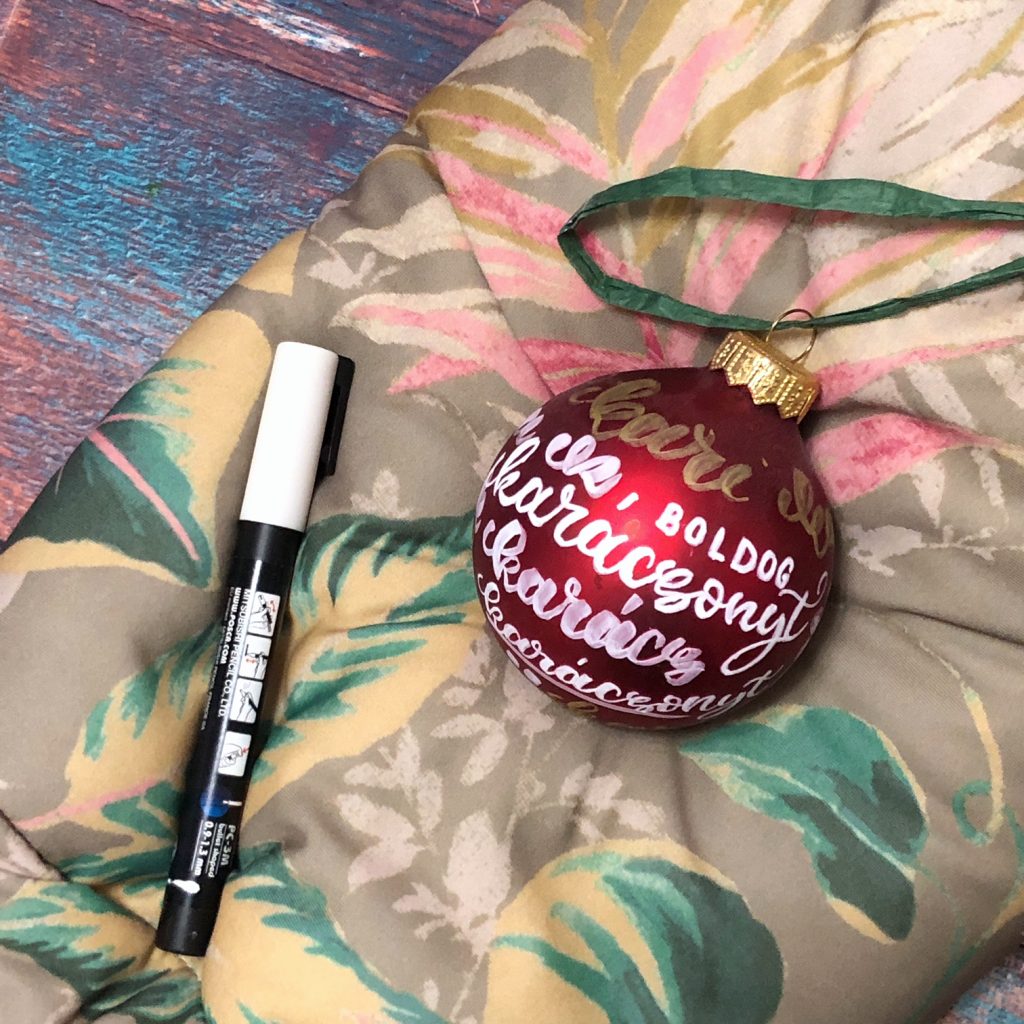
A díszítés
A karácsonyi gömbhöz ugyanazokat a trükköket fogjuk használni, mint korábban a bögrénél. Szóval, ahogy a bögrénél is írtam a lényeg, hogy találd meg azt a pozíciót, amivel alá tudod támasztani kezedet. Erre többféle verziót láttam, van, aki dobozokat tesz a keze alá, nekem a babzsák jött be igazán.
Ezután érdemes a fényes gömböknél alkohollal áttörölni felületet, hogy ne legyen rajta semmi zsír. Az íráshoz még érdemes valami kis könnyed kesztyűt használnod, hogy ahogy leérinted a kezedet ne legyen zsíros utána. A legegyszerűbb változat egy használt zokni kivágása úgy, hogy a gyűrűs és a kisujjad legyen benne. Nekem a Sheinről rendelt változat van, sok esetben hasznos.
Természetesen érdemes hamis kalligráfiát, akarom mondani letteringet használni. Kicsit meg is ugráltatni a betűket, mert így lehet „csalni” kicsit az egyenessel. A gömb esetében érdemes a pocakjára írni, azaz ahol a leghosszabb a körmérete, így itt van a legnagyobb felületet az írásra.
Érdemes akár a betűtípusokat keverni, mint ahogy én is tettem. Rád van bízva, hogy melyik verziót választod, nyilván függ attól is, hogy mennyi szöveget szeretnél ráírni. Összességében azért ezekre a 6-8 cm-es gömbökre maximum 1-2-3 szónál többet nem lehet írni, mert nem lesz túl olvasható, illetve neked is sokkal nehezebb dolgod lesz. Legalábbis ez a tapasztalatom, hogy a 4-5 mm-es ovális méret alatt egyre nehezebb az írás.
Szóval, ha meg van a szöveg, akkor helyezd a bögrét a zsákra és helyezkedj el az íráshoz. Ahogy írtam a bevezetőben is használhatsz akvarell ceruzát a skicceléshez, ha biztosra mennél. Ilyenkor a vastagítást ne húzd be, csak a szó sziluettjét! Ezután jöhet a filc, és a vastagítás. A Posca filcnél érdemes arra figyelni, hogy a vastagításhoz ne várd meg, hogy megszáradjon a festék, mert akkor csíkos lesz.
Még egy trükk, hogy ha jobbra rendezel egy szöveget, akkor érdemes jobbról visszafelé indítani, mert így biztosan kiférsz, illetve tudod azt is biztosítani, hogy egyforma távolságra legyenek a betűk. Egyéb esetben beszorulhatsz, és nem lesz egységes képe.
Fontos, hogy miután megírtad, hagyd megszáradni. Ha olyan dobozban érkezett, ami stabilan tartja, akkor csak óvatosan a tetejére tedd rá, ha nincs ilyen, akkor egy poharat szoktam használni erre célra úgy, hogy a felirat felfelé nézzen. A Posca filcek gyorsan megszáradnak. Ezeket bevallom nem szoktam fixálni, hiszen úgy is nagyon szoktunk a karácsonyi díszekre vigyázni, nem nagyon van kitéve semmilyen viszontagságnak.
Az alábbi videóban megmutatom, hogy én hogyan csinálom, a videó valós idejű, de ez nem azt jelenti, hogy neked is ilyen sebességgel kell írnod! Eddigre már igen sokadszorra kellett leírnom, szóval eléggé begyakoroltam. 😅
Csatolok egy sablont, ahol tudsz gyakorolni néhány verziót. Persze bármi mást is használhatsz, hiszen tudod a Faux letteringnél megbeszéltük, hogy akár használhatod a saját kézírásod, csak vastagítsd meg a lefele menő vonásokat, míg a felfelé menő vonásokat hagyd változatlanul.
Ezzel kész is a saját díszítésű karácsonyi gömböd!